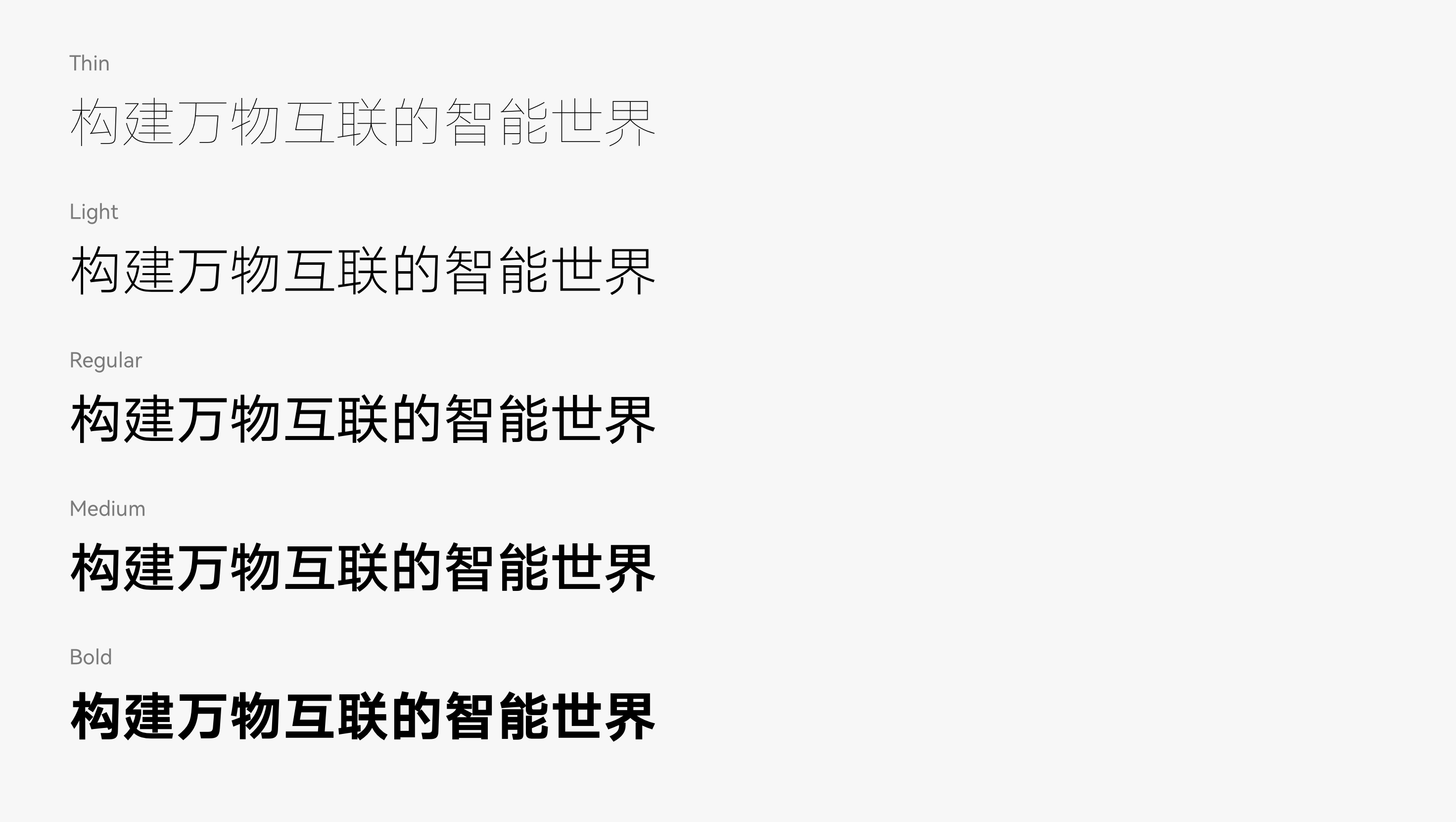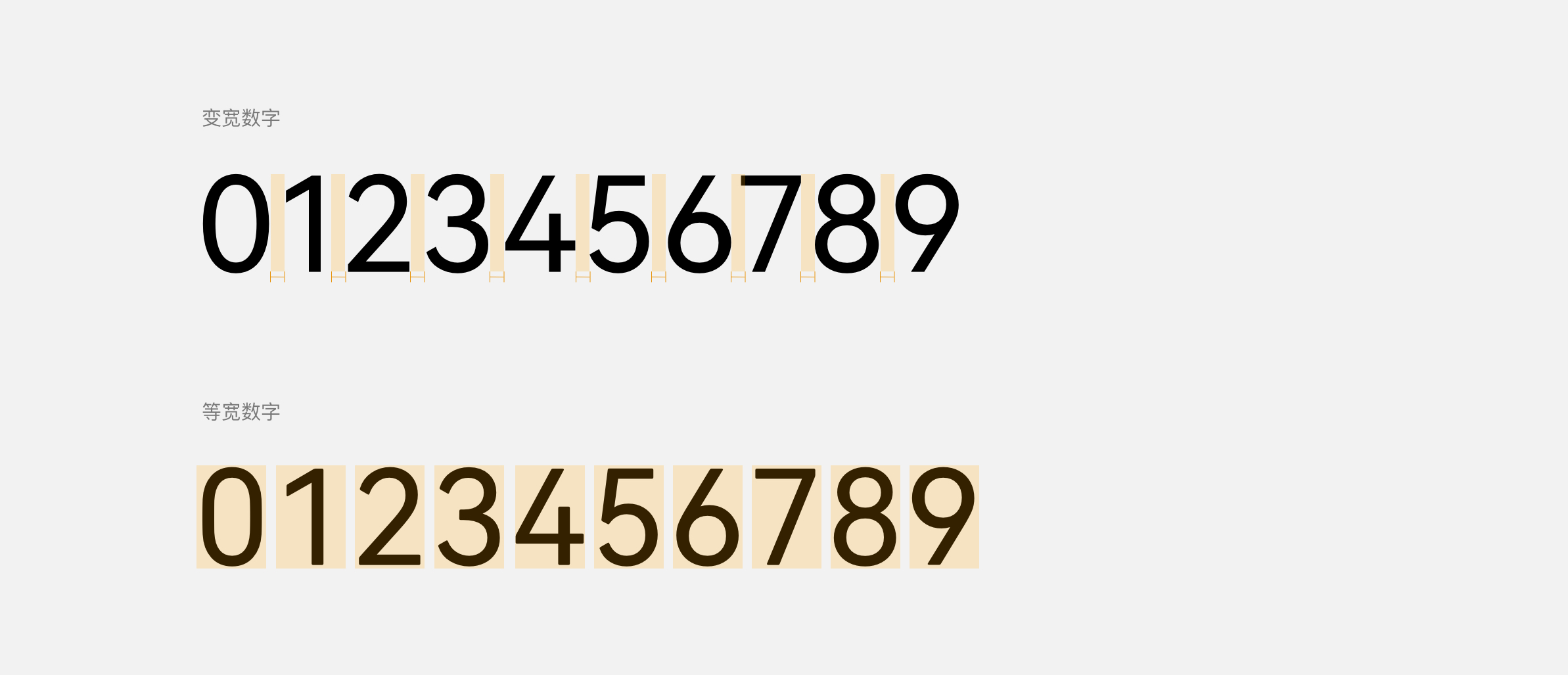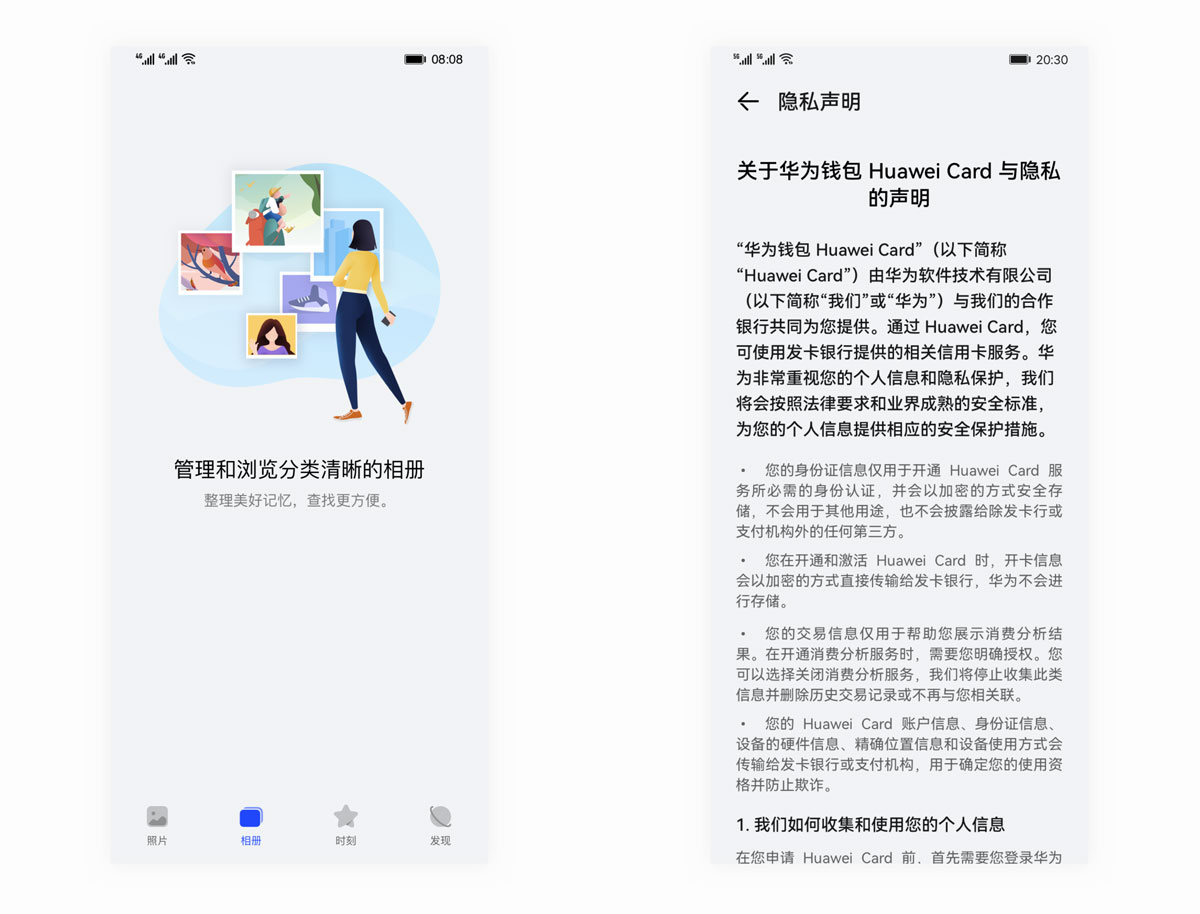
尽管我们主要将鸿蒙字体归类为简体中文字体,但它实际上还广泛支持中文繁体、阿拉伯语等语言。鸿蒙字体还拥有加高、斜体等不同样式,并具有六个不同的字重,是一款非常全面且优秀的字体。无论您需要设计什么样的作品,鸿蒙字体都能为您的作品增添独特的魅力。
全新设计:简约、书法、多语言
我们平衡了功能与美学,为全新字体设计简约无装饰的短笔画,同时融入书法的长笔画,展现笔势美学。优化灰度提升阅读体验,支持多语言让体验更一致。HarmonyOS Sans增加了Thin、Light、Bold、Black的字重能力,开发者可以选择需要的字重来构建界面的信息层级。
HarmonyOS Sans支持变宽和等宽两种样式。文本混排中使用系统默认的变宽数字,在阅读文本段落中能让阅读体验更加连贯。而等宽时钟数字在需要强调数值以及数据需要经常变化的表格和时钟数字的场景中使用时,可以保持数字字宽的对齐,同时更具图形化的呈现可以在界面中脱颖而出。